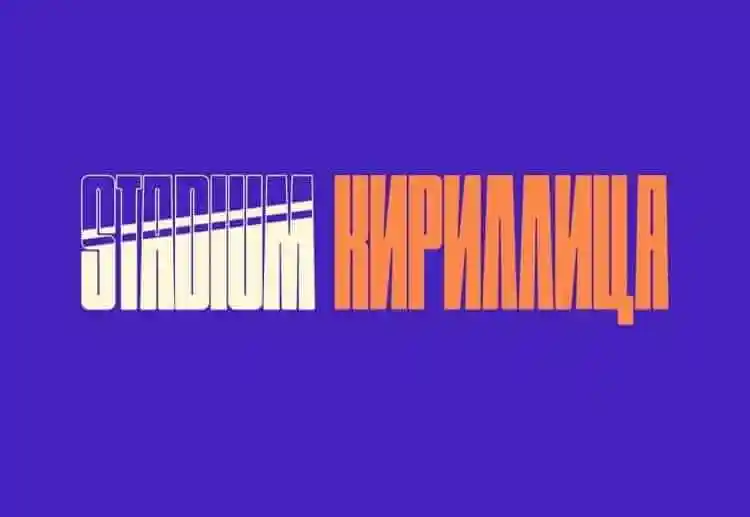
Esta font ‘Stadium Cyrillic Display’ é perfeita para quem busca uma opção artística para projetos que exigem destaque visual, como rótulos, capas e posteres. Ela oferece um x-altura mediana e baixa, o que a torna perfeitamente adequada para uso em tamanhos maiores de exibição. Suas linhas fortes e estruturais criam uma aparência elegante e moderna. Para projetos como rótulos ou embalagens criativos, esta font é ideal para escrever inscrições que destacarão seu design inovador. Não apenas é adequada para a tipografia em grandes superfícies visuais, mas também é perfeita para escritas mais menores e detalhadas. Uma escolha inteligente para designers buscando um estilo único e vibrante.